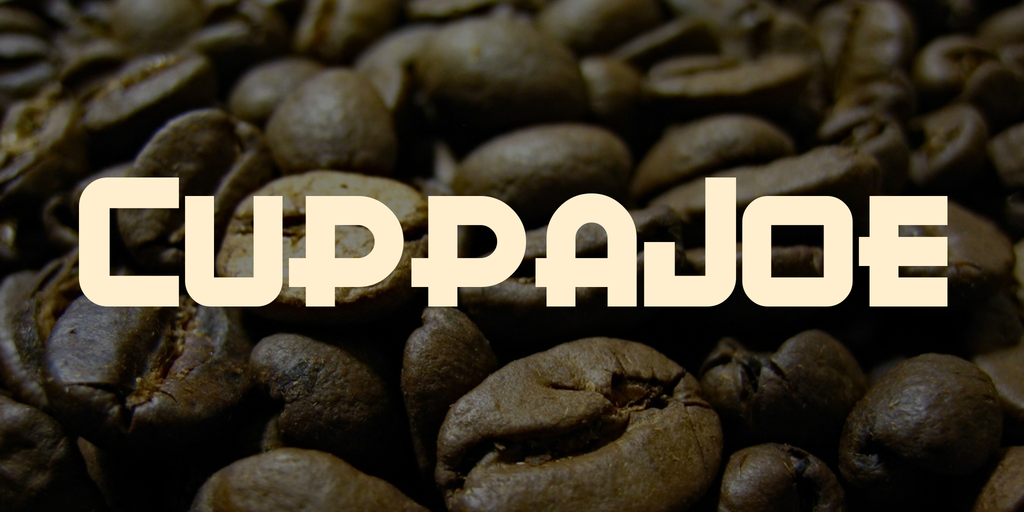
A fonte CuppaJoe é uma exuberante escolha para quem busca uma fonte display que transmite conforto e relaxamento sem abrir mão do charme moderno. Desenvolvida pelo designer Hamilton, essa fonte combina formas arredondadas e linhas suaves em um estilo casual e acolhedor que se destaca na categoria de fontes de exibição. Seja para o título de seu site ou para destacar suas mensagens promocionais, CuppaJoe traz uma paleta de gráficos vibrantes e personalizados, criando um visual atraente sem comprometer a legibilidade. Perfeita tanto para aplicativos móveis quanto para impressão digital, essa fonte não apenas torna sua marca mais visível, mas também transmite uma atmosfera descontraída e confortável que pode levar seu público a se sentir à vontade. Com CuppaJoe, é como adicionar um toque de calma a qualquer projeto visual sem deixar de lado o espírito inovador do design atual.